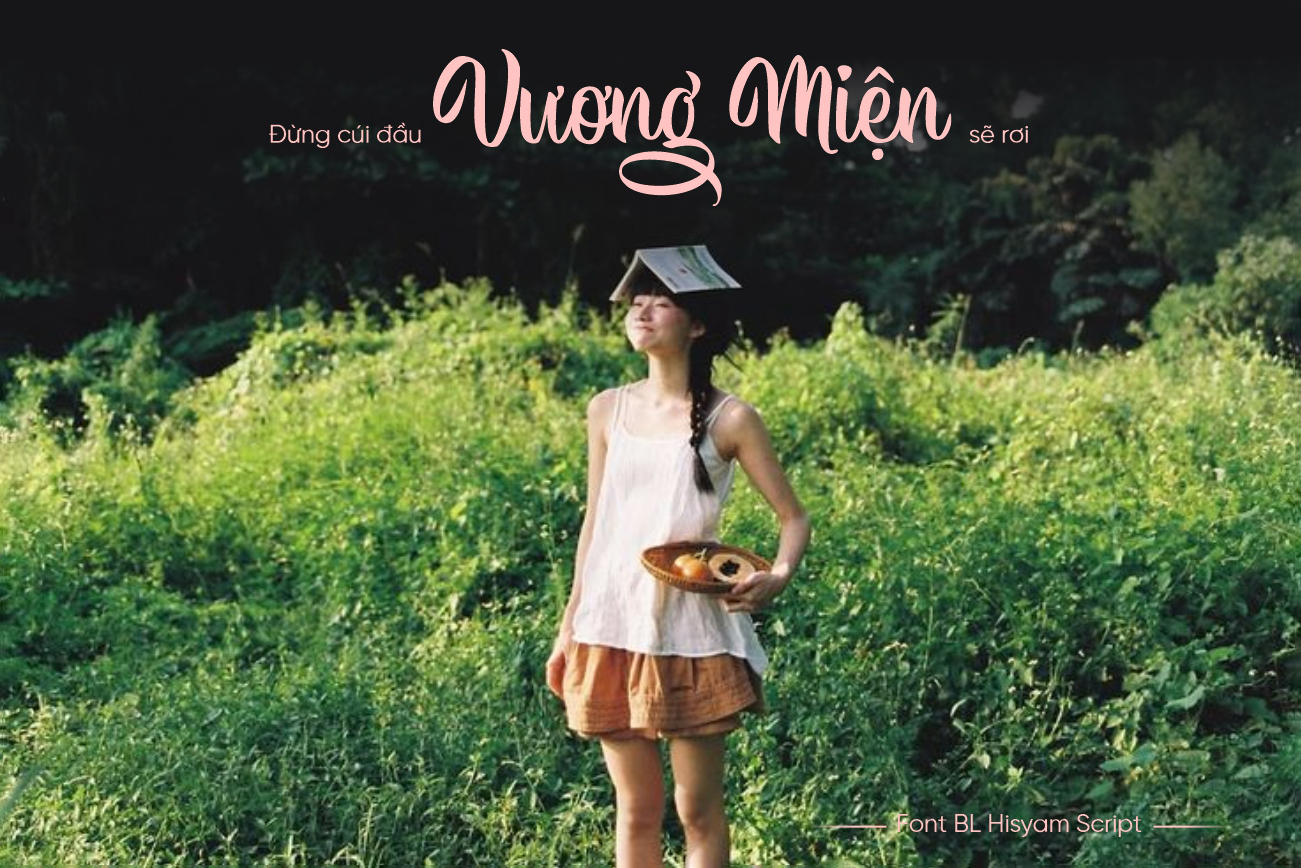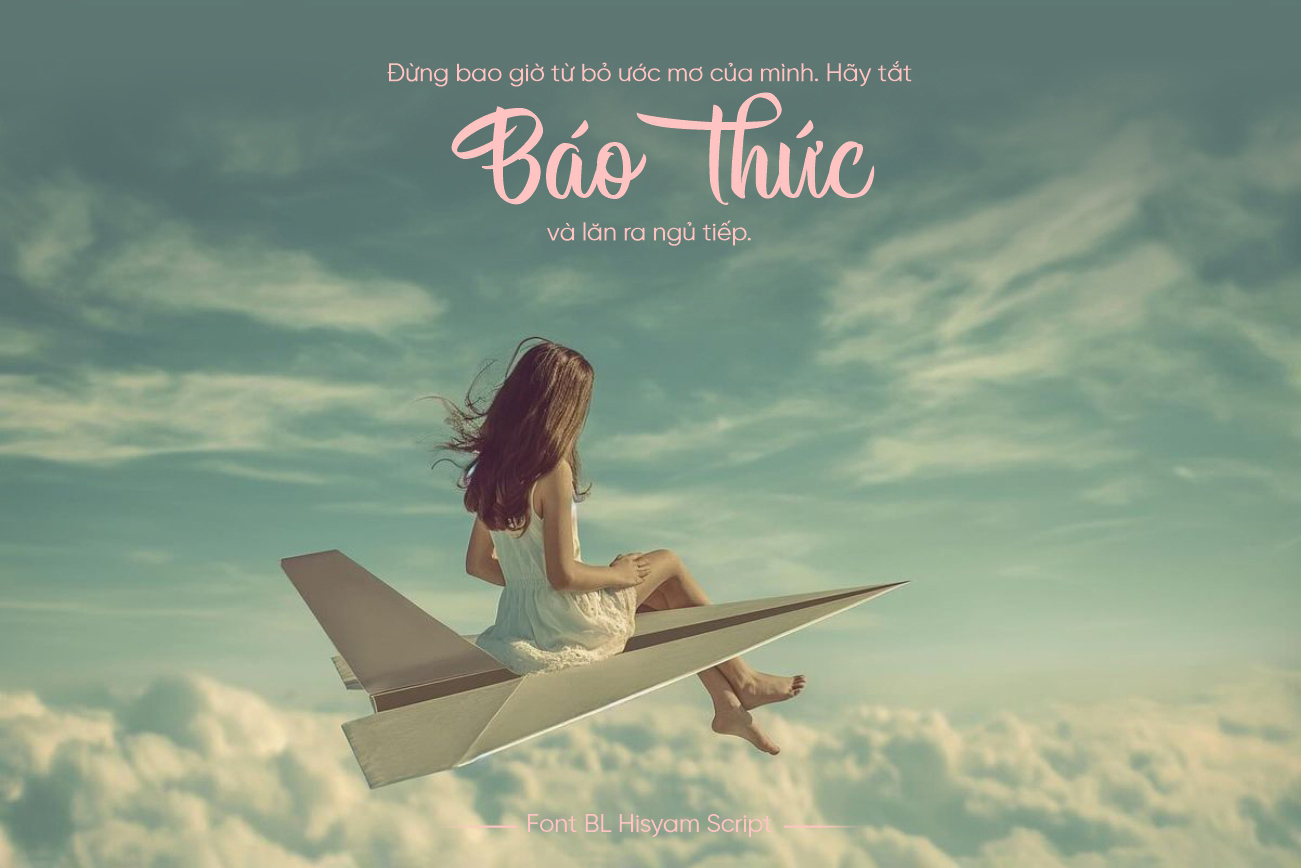
BL Hisyam Script - Font chữ nghệ thuật cho đám cưới
BL Hisyam Script là phiên bản Việt hóa từ bộ font Hisyam Script do Hendra Pratama thiết kế, mang tinh thần nghệ thuật mềm mại và giàu cảm xúc của phong cách chữ viết tay hiện đại. Ngay từ lần đầu tiếp xúc, bộ chữ tạo ấn tượng bởi vẻ ngoài uyển chuyển, tự nhiên và đầy tinh tế, thể hiện rõ chất font brush nét viết tay nghệ thuật tinh tế nhưng không quá phóng khoáng hay rối mắt. Phiên bản BL Hisyam Script được Team BL Việt hóa cẩn thận, tối ưu hệ thống dấu tiếng Việt để từng ký tự liền mạch, mượt mà và giữ nguyên được vẻ đẹp nguyên bản của thiết kế gốc, giúp font trở nên dễ sử dụng hơn trong các dự án sáng tạo tại Việt Nam.
Về kiểu dáng, BL Hisyam Script sở hữu những đường nét mềm mại, uyển chuyển như được viết bằng tay với cảm xúc nhẹ nhàng và có kiểm soát. Các nét bút có độ dày mỏng linh hoạt, tạo cảm giác chuyển động tự nhiên, vừa mang tinh thần của font brush, vừa thể hiện sự hiện đại, thanh lịch trong tổng thể hình dáng chữ. Chính sự cân bằng này giúp BL Hisyam Script phù hợp cho nhiều mục đích sử dụng khác nhau như logo thương hiệu, poster nghệ thuật, thiệp cưới, thiệp chúc mừng, bao bì sản phẩm hoặc các thiết kế truyền thông cần yếu tố cảm xúc và tính thẩm mỹ cao. Khi đặt trong bố cục, bộ chữ mang lại cảm giác gần gũi, cá nhân nhưng vẫn rất chỉn chu và sang trọng.
Nguồn gốc của Hisyam Script được xây dựng từ cảm hứng về chữ viết tay mang tính cá nhân, nơi từng con chữ không chỉ truyền tải thông tin mà còn thể hiện phong cách và cảm xúc của người viết. Khi được Team BL Việt hóa thành BL Hisyam Script, bộ font không chỉ giữ nguyên tinh thần nghệ thuật đó mà còn được hoàn thiện hơn để phù hợp với tiếng Việt, giúp người dùng khai thác dễ dàng trong nhiều loại hình thiết kế.
Nếu bạn đang tìm một bộ chữ mang đậm chất font brush nét viết tay nghệ thuật tinh tế, kết hợp hài hòa giữa sự mềm mại và vẻ hiện đại, thanh lịch, BL Hisyam Script chắc chắn là lựa chọn đáng cân nhắc để nâng tầm thẩm mỹ và tạo dấu ấn riêng cho mọi dự án sáng tạo.